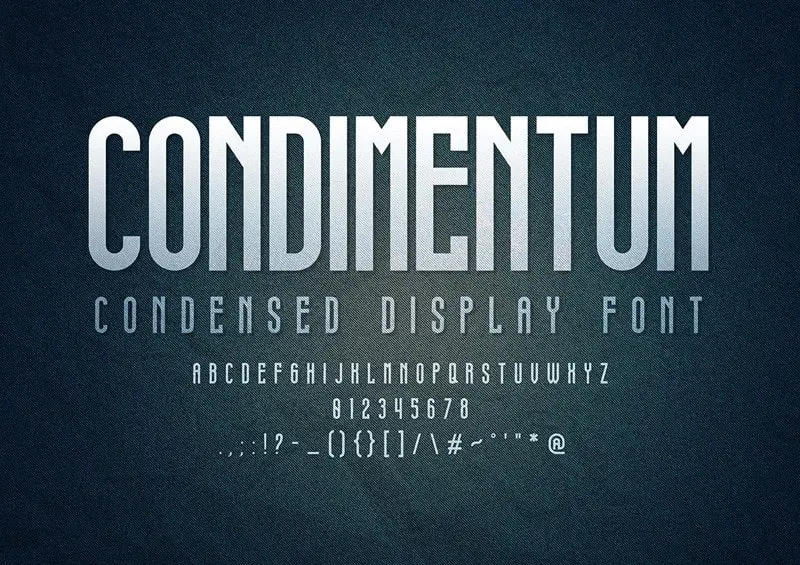
Condimentum Display Font – Download Grátis
Condimentum Display Font é uma tipografia exibição moderna inspirada nos tempos soviéticos, com letras maiúsculas e minúsculas, números e símbolos. Esta fonte de estilo display oferece a oportunidade perfeita para projetar cards de aniversário ou embalagens, criar identidades de marca, designs DIY, títulos de livros, fontes para casamentos vintage, designs retro e muito mais, proporcionando um toque moderno e trendy aos seus trabalhos artísticos ou design. A Condimentum Display Font é uma opção perfeita para quem busca dar um brilho único a qualquer projeto visual.